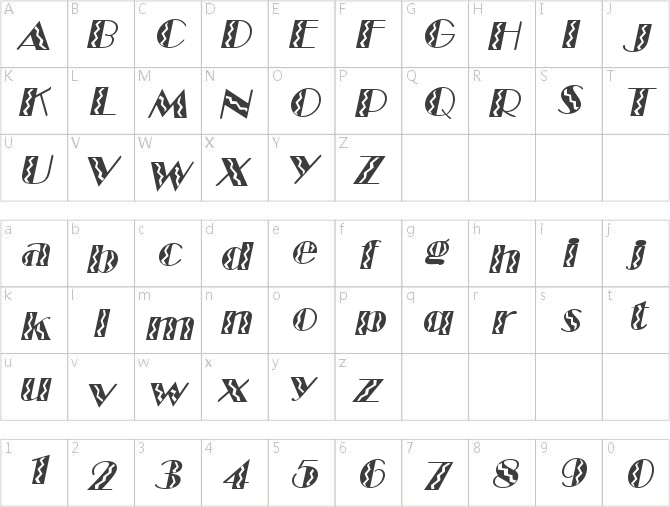
marqueeflashitalic 詳情頁
字體名稱: marquee
marqueeflashitalic
marqueeflashitalic字體字庫是一款讓人賞心悅目、百看不厭的英文字體,適合各類廣告和產品包裝設計應用,字體大小0.06MB,格式為ttf字體,上傳用戶是后天的昨天,作者/版權方為未知